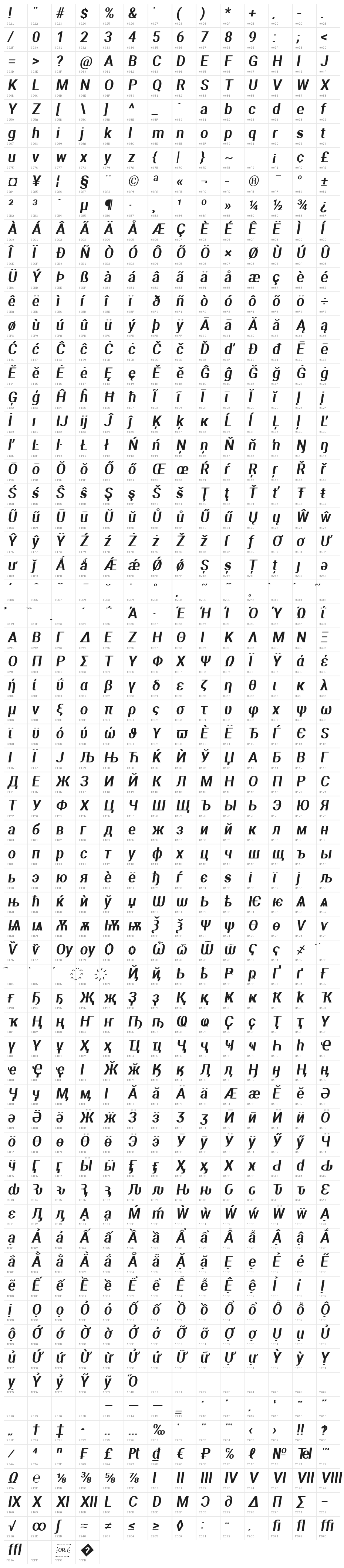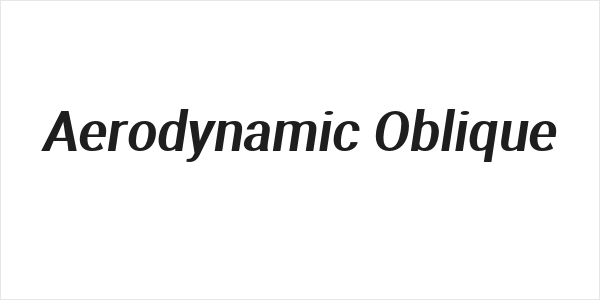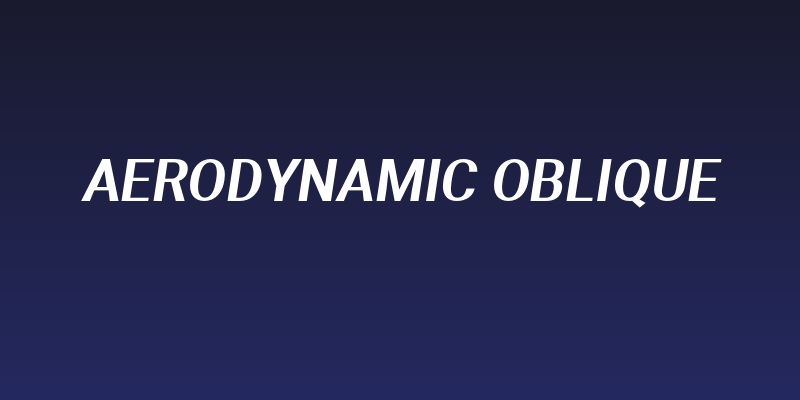
Aerodynamic Oblique Font
| Caso d'uso | Headlines, Logos, Advertisements |
| Progetti proposti | Ideal for branding, sports-related designs, automotive advertisements, and modern web design. |